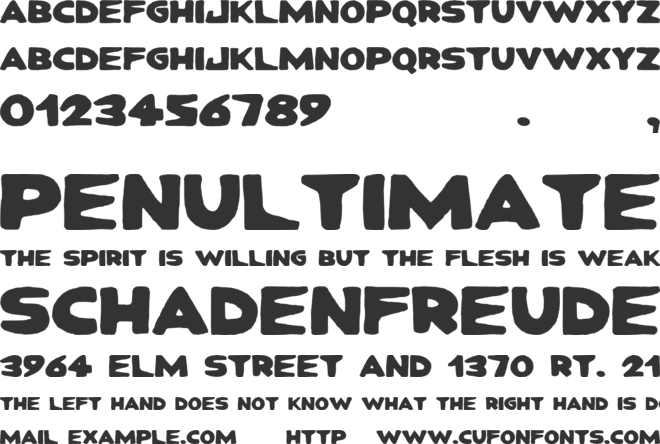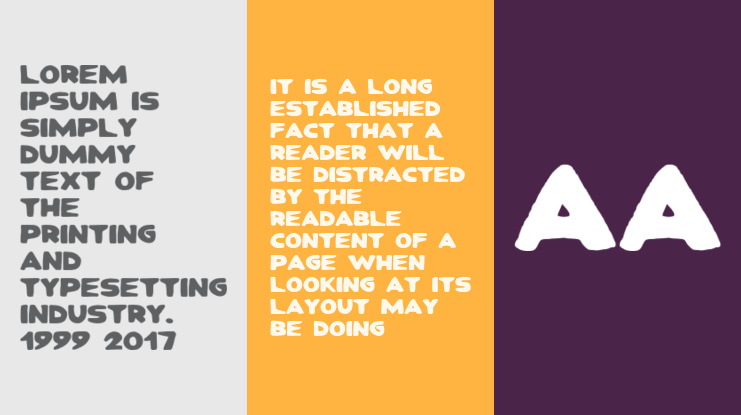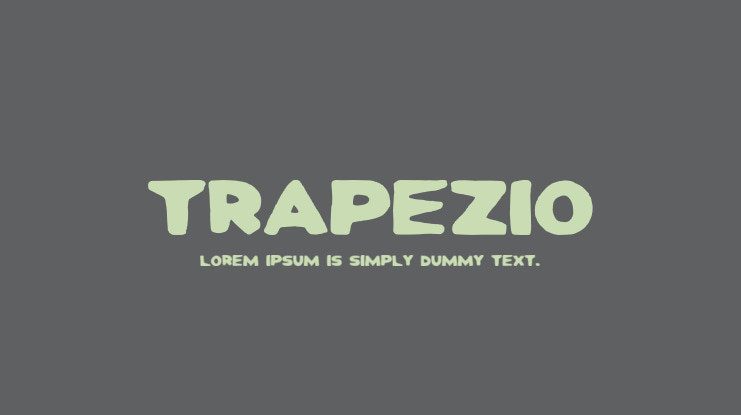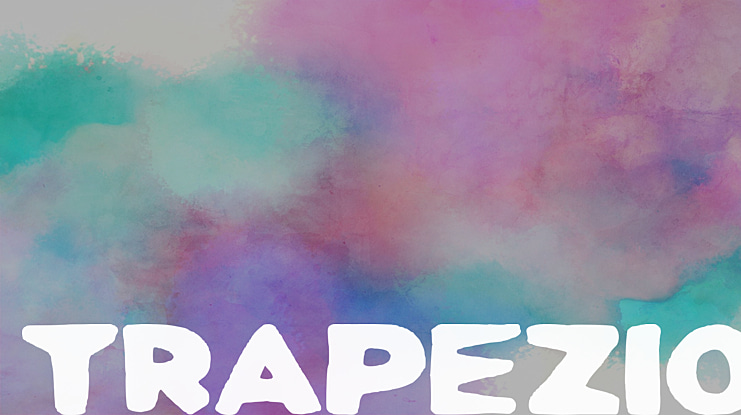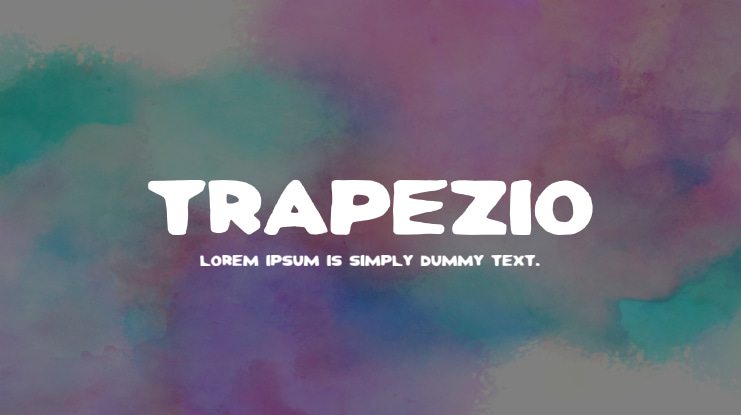
Trapezio Font
P.A.Vannucci
Direttamente dal film diretto da Carol Reed e interpretato da Gina Lollobrigida, il font inedito per tutti gli estimatori del film.
Directly from the film directed by Carol Reed and starring Gina Lollobrigida, the unpublished font for all admirers of the film.